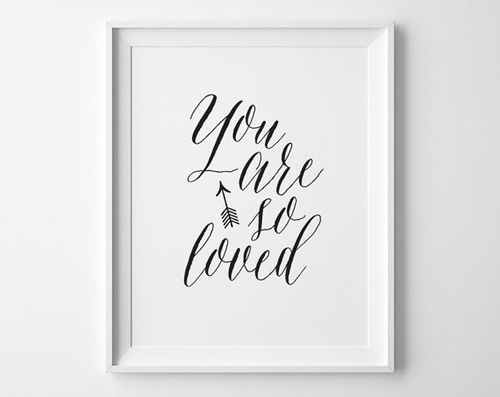
[Шрифт] Asterism - Рукописный красивый шрифт
Красивые, а главное - продающиеся работы получаются этим шрифтом:
Врачи бесплатно им обладают. :)
Где бы кириллицу похожую найти. Хотя бы название.
классный шрифт!